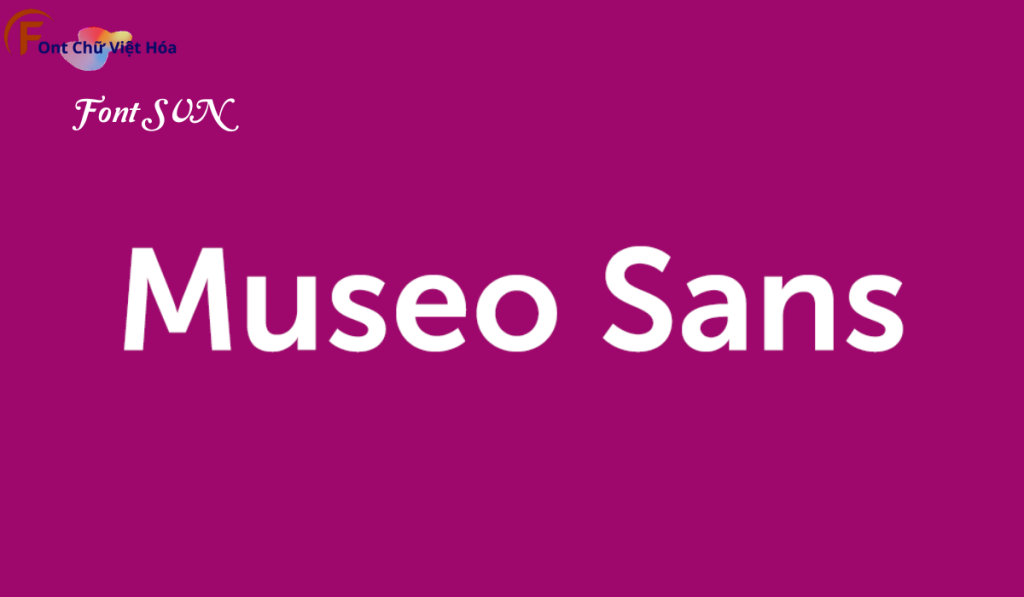
Font SVN Museo Sans Việt Hóa
Phân loại: Cá tính, Hiện đại
Độ dày: Mỏng, Bình thường, Đậm
Font SVN Museo Sans Việt Hóa là một font chữ không chân hiện đại, thuộc bộ font SVN. Được thiết kế với mục tiêu mang lại sự tinh tế và thanh lịch, font này phù hợp cho các dự án thiết kế như website, tài liệu, và bao bì sản phẩm. Với các nét chữ rõ ràng và độ dày đều đặn, Font SVN Museo Sans Việt Hóa không chỉ dễ đọc mà còn tạo cảm giác chuyên nghiệp. Việc Việt hóa font giúp người dùng dễ dàng sử dụng trong các thiết kế tiếng Việt, mang lại sự tiện lợi và thẩm mỹ cao.